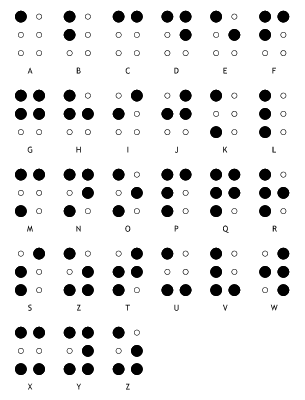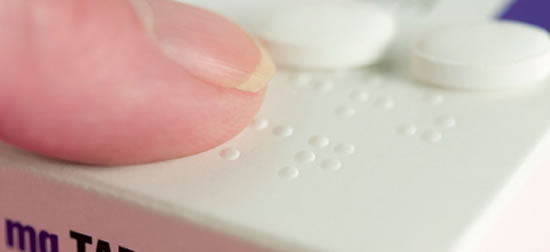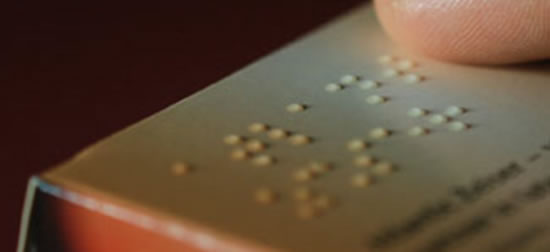
Braille jest rozpoznawalnym w świecie systemem zapisu i odczytu informacji dla niewidomych i niedowidzących. System ten został wymyślony w 1852 przez Louisa Braille'a (1809-1852), który żył we Francji i stracił wzrok w wieku 3 lat.
Zapis Braille'a nie jest językiem, jest odmiennym sposobem zapisu i odczytu znaków. Znaki są reprezentowane przez układ wypukłych punktów. Na każdy ze znaków (tzw. komórkę) składa się sześć kropek ułożonych w kształcie prostokąta posiadającego dwie kolumny po 3 kropki. Punkt może być wzniesiony na każdej z 6 pozycji tworząc wiele różnych kombinacji. Istnieje 64 takich wariantów (wliczając spację, gdy żaden z punktów nie jest uniesiony). Dla celów łatwiejszego rozpoznawania, każda kombinacja może być opisana poprzez określenie pozycji, w których punkty są uniesione. I tak punkty w lewej kulumnie mają odpowiednio numery (z góry na dół) 1, 2 i 3 a w prawej kolumnie (z góry na dół) 4,5 oraz 6. Tak więc znak o punktach 1-3-4 posiada komórkę w której 3 punkty są uniesione: najwyższy i najniższy w lewej kolumnie i najwyższy w prawej kolumnie (litera „M”).
Sposób budowania kolejnych znaków alfabatu Braille'a. |
Istnieje wiele specyfikacji składania znaków Braille'a. Jednakże fonty PharmaBraille (cały ich zestaw) spełnia postanowienia specyfikacji Marburg Medium, jako rekomendowanej przez Komisję Europejską, standardy Can-Am Braille oraz ECMA EuroBraille dla przygotowania opakowań i oznaczeń dla niewidomych dla produktów farmaceutycznych.
Specyfikacja systemu Braille według wytycznych Marburg Medium
- Średnica punktu 1.3-1.6mm
- Odstępy między punktami 2.5mm (mierzone od środków punktów)
- Odstępy między znakami 6.0mm (mierzone od środków punktów)
- Odstęp między kolejnymi linaimi tekstu 10.0mm.
Konwencja spacjowania sytemu Marburg Medium oraz wymiary znaków Braille'a dla matrycy wklęsłej (patrycy) oraz dla klisz fotograficznych i plików elektronicznych. |
Legenda Tolerancja: ±0.1mm
- 2.5mm
- 6.0mm pomiędzy dwoma znakami
- 12.0mm odstępy międzywyrazowe
- 10.0mm odstępy między kolejnymi wierszami
Może się zdażyć, że podanych tu wartości nie da się osiągnąć w praktyce. W zależności od podłoża i stosowanej techniki wytłaczania (lub nanoszenia punktów) tolerancja może nie być zachowana, np. odstępy między kolejnymi wierszami przy stosowaniu podawania nalepek z taśmy z perforacją (tzw. traktora) gdzie górne wartości odstępów są często przekraczane.
Każdy kraj posiada swój własny kod Braille'a. Są pewne podobieństwa ale też i wyraźne różnice. Stąd też fonty Braille'a PharmaBraille są dostarczane z odpowiednim kodowaniem i formacie dla danego kraju.
Każdy zestaw językowy zawiera po 3 fonty: PharmaBraille Regular, PharmaBraille Grid oraz PharmaBraille Letter czyli wszystko czego można potrzebować przy projektowaniu opisów opakowań w zastosowaniach farmaceutycznych.
PharmaBraille Regular |
PharmaBraille Grid |
PharmaBraille Letter |
Ten rodzaj jest używany w procesie wytłaczania opakowań farmaceutycznych. |
Bardzo przydatny przy kontroli wizualnej spacjowania. |
Podgląd wizualny przy sprawdzaniu znaków poza obszarem wykrojnika. |
Pełen zestaw fontów PharmaBraille Zawiera wszystkie 26 zestawów narodowych: Anglia i Irlandia, Ameryka Północna (Can-Am Braille), European Blind Union Medicinal Braille, Francja, Niemcy, Włochy, Hiszpania, Portugalia, Holandia, Dania, Norwegia, Finlandia, Szwecja, Polska, Czechy Słowakia, Słowenia, Grecja, Węgry, Bułgaria, Rosja, Ukraina, Rumunia, Estonia, Łotwa oraz Islandia.
Transkrypcja Braille Istnieje możliwość zapisu alfabetem Braille'a tekstu tylko poprzez zamianę znaku alfabetu łacińskiego na odpowiadający mu znak systemu Braille'a - system taki, zwany Klasą 1 (Grade 1 Braille), jest stosowany prez początkujących użytkowników. Jednak z tego samego powodu (łatwość zrozumienia) Klasa 1 jest rekomendowana przy tworzeniu opakowań medycznych i farmaceutycznych.
Znaki alfabetu Braille'a zajmują dużo więcej miejsca niż ich standardowe odpowiedniki literowe i na standardowej stronie o wymiarach 28cm × 28cm mieści się tylko 25 linii po 40 znaków. Aby więc zredukować zajmowane miejsce i zwiększyć szybkość czytania prawie wszystkie książki składane alfabetem Braille'a są konwertowane na tzw. Klasę 2 (Grade 2 Braille), która wykorzystuje system skrótów. Podobnie jak większość zaawansowanych czynności językowych, używanie języka Braille'a Klasy 2 wymaga skomplikowanego przygotowania. Instrukcje dotyczące używania tego systemu w Bibliotece Kongresu Library mają podad 200 stron zaleceń i wskazówek. Przekład zapisu Braille'a z Klasy 1 na Klasę 2 jest procesem wymagającym dużej umiejętności i musi przechodzić przez wiele testów weryfikacyjnych.
Klasa 3 (Grade 3 Braille) jest systemem, który zawiera jeszcze więcej dodatkowych skrótów, prawie „ocierających” się o stenografię. Nie używa się go w publikacjach i jest najczęściej stosowany lokalnie przez poszczególnych użytkowników.
Zalecenia tworzenia opakowań farmaceutycznych rekomendują stosowanie Klasy 1 (Grade 1 Braille - tzw. „niezagęszczony” Braille).